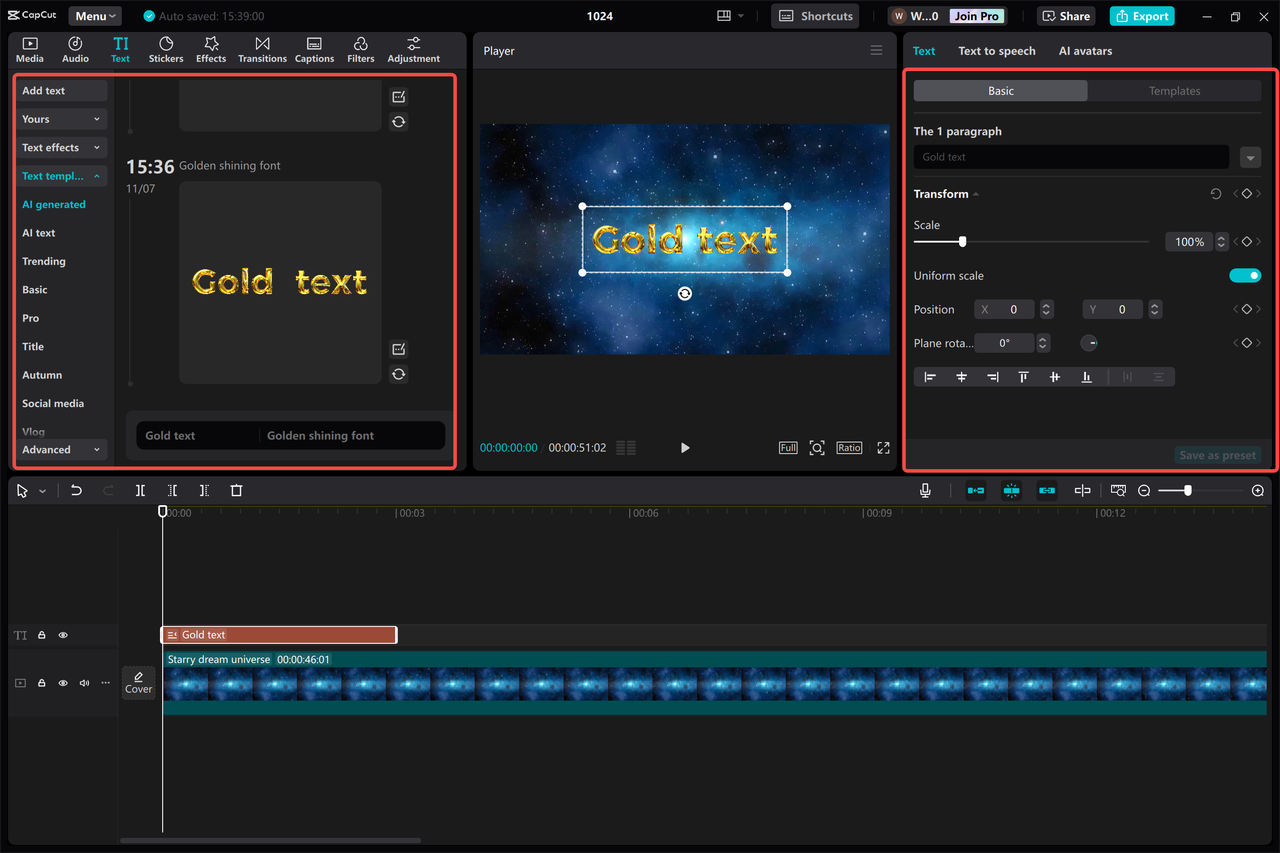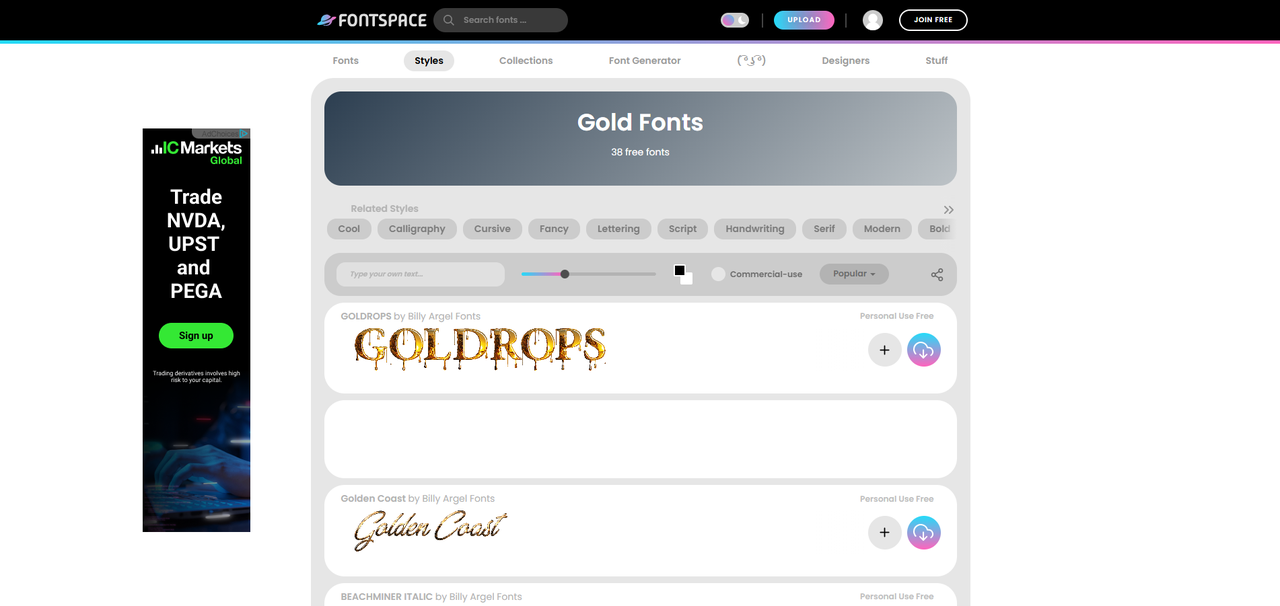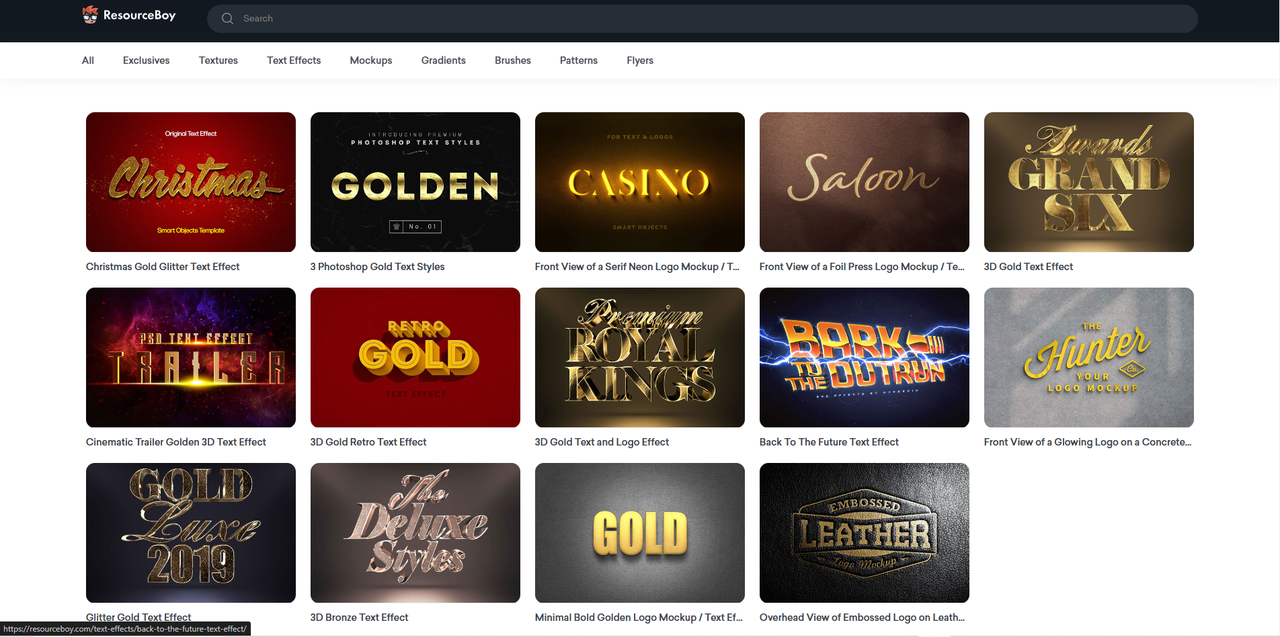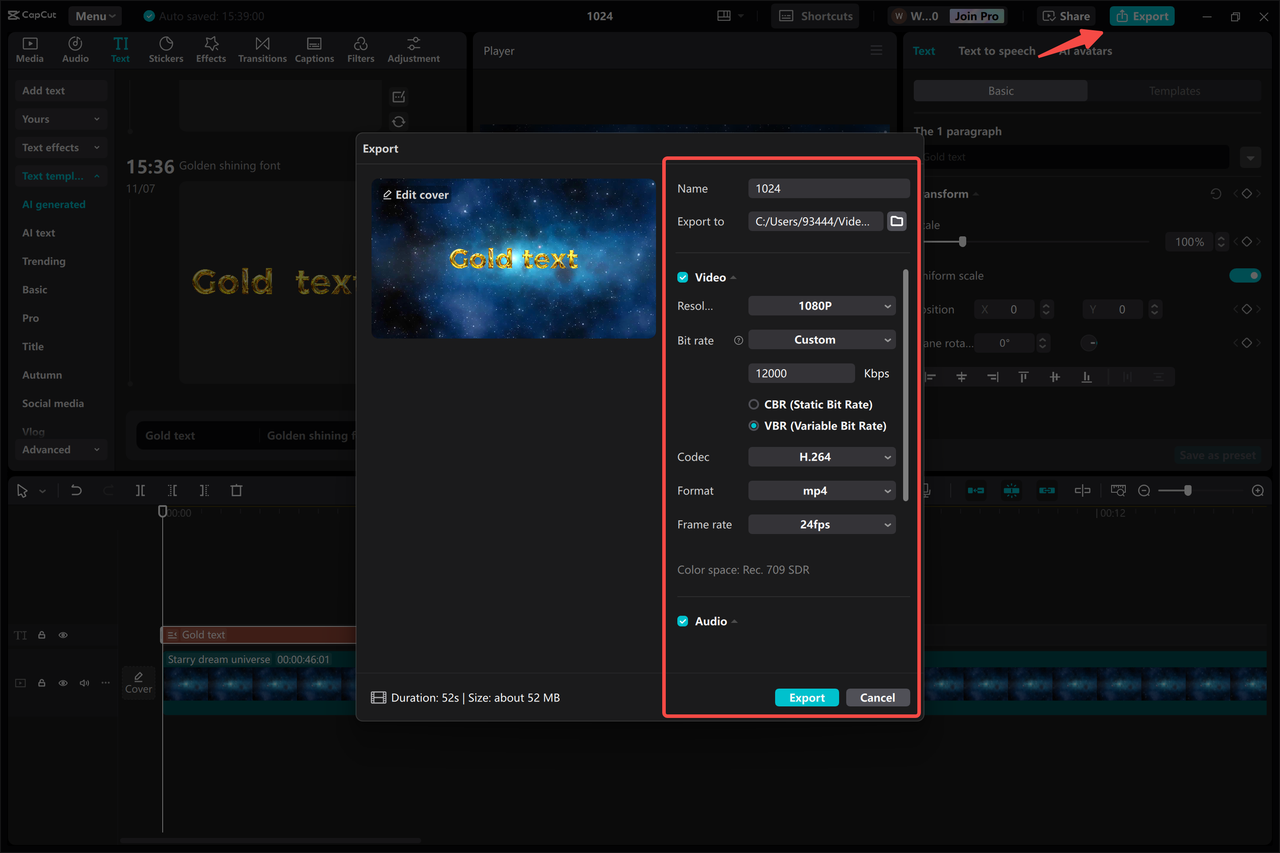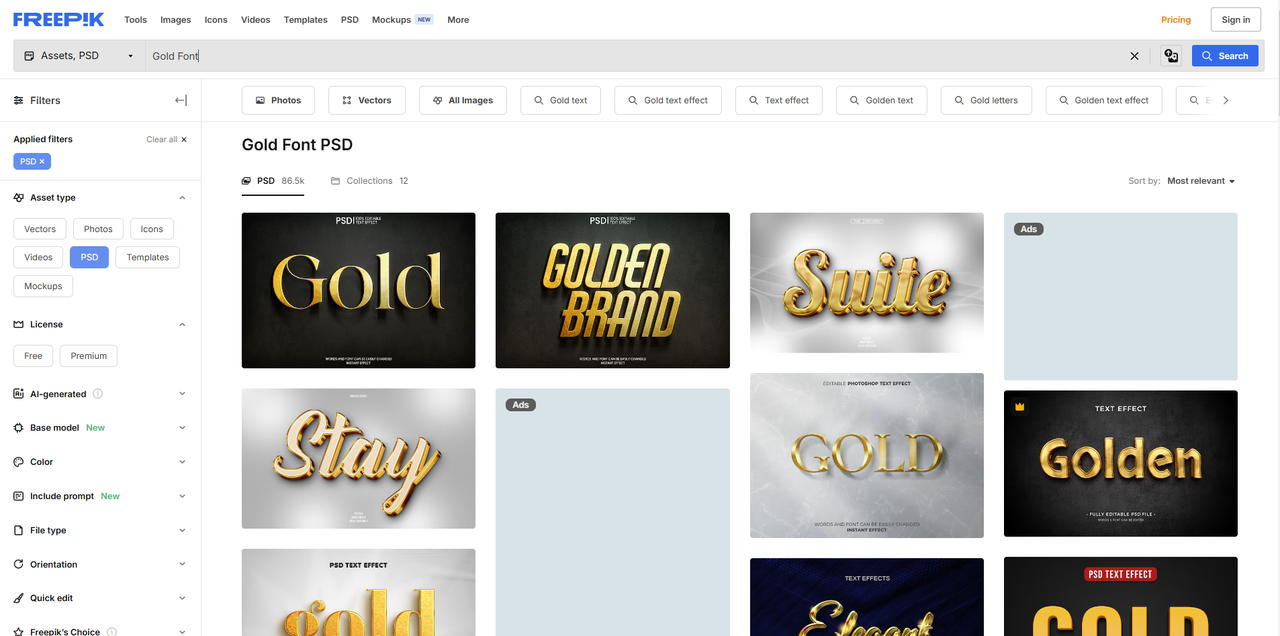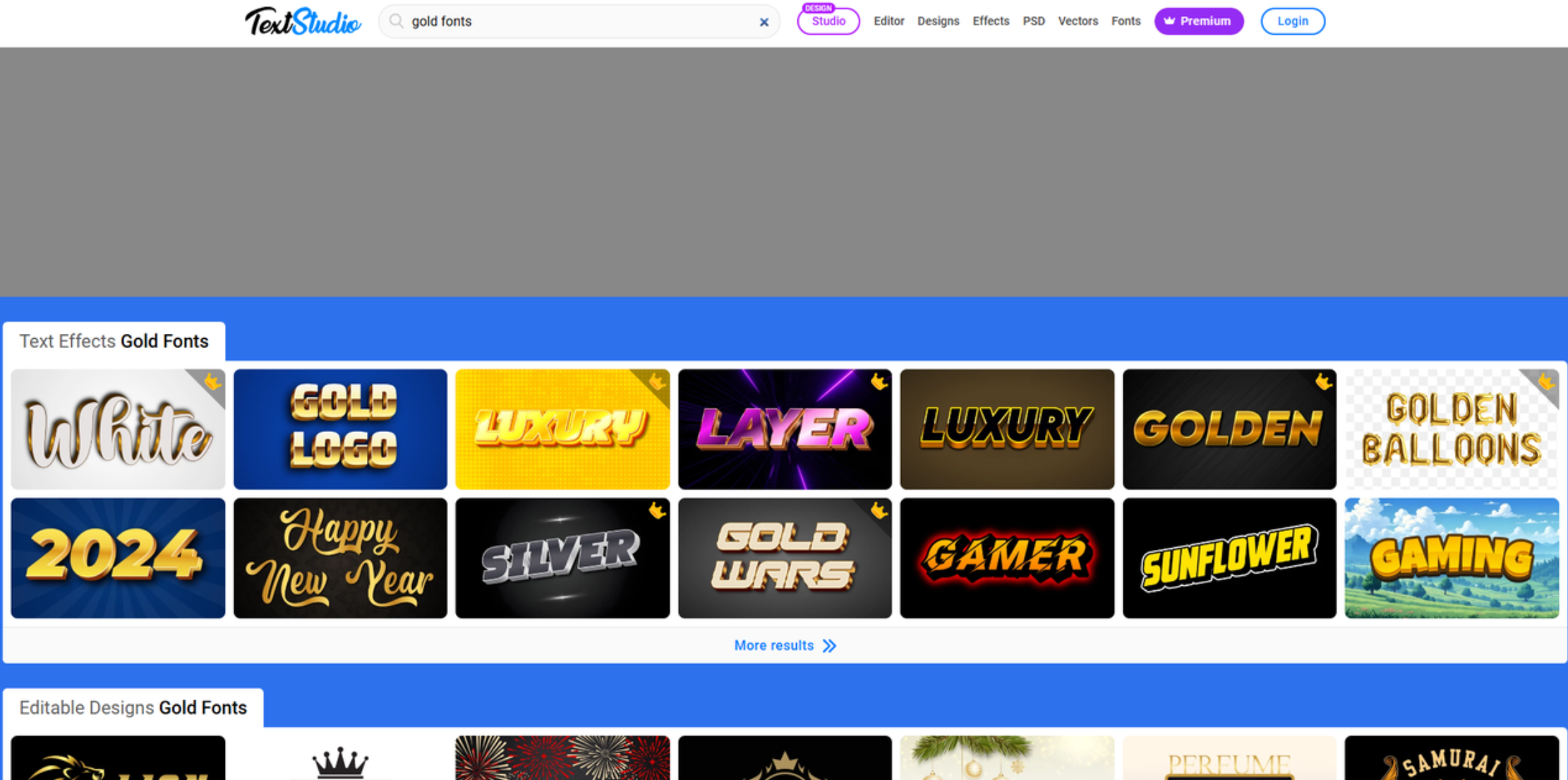
الدليل النهائي لاستخدام الخطوط الذهبية | جعل التصاميم الإبداعية
استكشف خطوط الذهب الرائعة وتعلم كيفية رفع تصميماتك باستخدام الطباعة الجذابة. أضف لمسة من الفخامة إلى رسوماتك بسهولة. علاوة على ذلك ، جرب محرر فيديو سطح المكتب CapCut لتطبيق تأثيرات النص الذهبي السلسة على مقاطع الفيديو وضبطها.
خطوط الذهب
يعد اختيار الخط الصحيح أمرًا مهمًا لكيفية تلقي رسالتك في التصميم والطباعة. تعد الخطوط الذهبية خيارًا شائعًا لإضافة الأناقة والرقي إلى مشاريعك. إنها مثالية للمناسبات التي تريد أن تترك فيها انطباعًا دائمًا.
في هذه المقالة ، سنلقي نظرة على بعض الأفكار الإبداعية لاستخدام نص ذهبي وبعض أفضل الأدوات لتوظيفها لإضافتها إلى المحتوى الخاص بك.
رفع مظهر التصميم الخاص بك مع ألوان الخط الذهب
الآن بعد أن رأينا كيف يمكن أن تكون نصوص الألوان الذهبية جذابة في تصميماتنا ، فلنتعلم كيفية استخدامها بفعالية. تؤدي إضافة هذا النص إلى مشاريعك إلى تباين قوي مع الخلفيات المختلفة ، مما يجعل المحتوى الخاص بك بارزًا. سننظر في عدة طرق لاستخدام النص الذهبي لتحسين تصميمك وإشراك جمهورك!
5 أفكار الخط الذهب الإبداعية
عندما تختار حروفًا ذهبية ثلاثية الأبعاد لتصميماتك ، فإن لكل نمط فوائده بناءً على ما تريد تحقيقه. يمكن للخط الصحيح تحسين مظهر أي شيء ، من الدعوات الرسمية إلى العلامات التجارية الحديثة. فيما يلي 5 أفكار إبداعية لاستخدام النص الذهبي ثلاثي الأبعاد بشكل فعال:
1. سيناريو أنيق للدعوات
يعد استخدام النص الذهبي في نص أنيق خيارًا كلاسيكيًا للدعوات ، خاصة لحفلات الزفاف والمناسبات الرسمية. تضيف الخطوط المتدفقة لخطوط النص الرومانسية والرقي ، مما يجعل دعوتك تشعر بالخصوصية. هذا النمط يعزز الأناقة الشاملة لإعلانات الزفاف.
1. جريئة الرقيق للعلامة التجارية
تعتبر الخطوط الرقيقة الجريئة المصنوعة من الذهب رائعة للعلامة التجارية لأنها تنقل القوة والموثوقية. يمكن أن تؤدي إضافة تأثير نص ذهبي ثلاثي الأبعاد إلى تحسين الرؤية ، مما يمنح علامتك التجارية ميزة فريدة. سواء كان إطلاق منتج جديد أو تغيير العلامة التجارية ، يمكن لخطوط serif الجريئة إنشاء هوية قوية تتواصل مع جمهورك.
1. نمط خمر لتصاميم الرجعية
لإحساس بالحنين إلى الماضي ، تعد الخطوط ذات النمط القديم باللون الذهبي خيارًا جيدًا. غالبًا ما تذكر هذه الخطوط الأشخاص بالماضي وتعمل بشكل جيد مع الحفلات ذات الطابع الخاص أو العلامات التجارية القديمة. يمكن أن يؤدي استخدام خط ذهبي ثلاثي الأبعاد إلى إبراز الخطوط القديمة ، مما يضيف العمق والاهتمام.
1. Sans-serif لجماليات الحد الأدنى
إذا كنت تفضل أسلوبًا نظيفًا وحديثًا ، فإن خطوط sans-serif المصنوعة من الذهب مناسبة للتصاميم البسيطة. هذه الخطوط بسيطة وسهلة القراءة ، مما يجعلها رائعة لمواقع الويب ووسائل التواصل الاجتماعي والعلامات التجارية الحديثة. علاوة على ذلك ، فهو يعمل بشكل جيد مع العلامات التجارية التي ترغب في إظهار صورة حديثة.
1. مكتوبة بخط اليد لمسات شخصية
تضيف الخطوط الذهبية المكتوبة بخط اليد لمسة شخصية لأي تصميم. إنه ممتاز لبطاقات المعايدة أو المدونات الشخصية حيث تريد التواصل مع جمهورك. يمكن أن يؤدي استخدام PSD للنص الذهبي ثلاثي الأبعاد هنا إلى جعل النص يبدو ديناميكيًا وجذابًا.
أفضل 5 طرق مفيدة لتنزيل تأثيرات النص الذهبي المجانية
توفر العديد من الموارد عبر الإنترنت تنزيلات مجانية لتأثيرات النص الذهبي الجميلة. باستخدام هذه التأثيرات ، يمكنك تحسين مشاريعك بسرعة وجعلها تبدو أفضل. فيما يلي 5 طرق مفيدة لتنزيل تأثيرات النص الذهبي المجانية لاحتياجاتك:
1. CapCut محرر فيديو سطح المكتب
يعد محرر فيديو سطح المكتب CapCut أداة سهلة الاستخدام لإنشاء مقاطع فيديو رائعة. يحتوي على العديد من الميزات ، بما في ذلك الرسوم المتحركة النصية الذهبية الأنيقة والتأثيرات التي يمكن إضافتها إلى أي محتوى فيديو. من خلال تخطيطه البسيط ، يمكنك تخصيص النص بسرعة وجعل مقاطع الفيديو الخاصة بك جذابة بصريًا. يحتوي هذا البرنامج أيضًا على أدوات تخصيص فيديو أخرى للحصول على مظهر نهائي محسّن.
Interface of the CapCut desktop video editor - an easy way to add gold text to videos on PC
السمات الرئيسية
يحتوي محرر فيديو سطح المكتب CapCut على العديد من الميزات التي تسهل إضافة نص إلى مقاطع الفيديو الخاصة بك . فيما يلي بعض من أفضلها:
• المدمج في تأثير النص الذهب
تطبيق على الفور جميلة تأثيرات النص الذهب لمشاريعك ، إضافة لمسة من الأناقة دون الحاجة الإضافات إضافية.
• قابل للتعديل الظل وخيارات توهج
قم بتحسين رؤية النص الخاص بك عن طريق تخصيص إعدادات الظل والتوهج ، وخلق العمق ، وجعل النص الذهبي الخاص بك بارزًا.
• الانتهاء من المعدن مع وسائط مزيج
حقق مظهرًا معدنيًا واقعيًا للنص باستخدام أوضاع مزج مختلفة ، مما يتيح لك مطابقة التأثير مع خلفيات مختلفة بسلاسة.
• تحرير نص طبقة مرنة
قم بتحرير طبقات النص وترتيبها بسهولة في مشروعك ، مما يمنحك تحكمًا كاملاً في التصميم ويضمن وضع النص الذهبي بشكل مثالي.
• مواضع نص مخصص
ضع النص الذهبي في أي مكان على الشاشة بدقة. يضمن ذلك تخطيطات إبداعية تعزز جمالية الفيديو بشكل عام ، خاصة عند إضافة ترجمات مصاحبة إلى الفيديو .
كيفية إضافة الخطوط الذهبية إلى مقاطع الفيديو في CapCut
لإضافة خطوط ذهبية إلى مقاطع الفيديو الخاصة بك في CapCut ، قم أولاً بتنزيل البرنامج وتثبيته من الموقع الرسمي. بمجرد التثبيت ، افتح CapCut وأنشئ مشروعًا جديدًا. يمكنك بسهولة تطبيق الخطوط الذهبية عن طريق تحديد خيارات النص وتخصيصها بالتأثيرات المضمنة. يمكنك تنزيله بالنقر فوق زر التنزيل أدناه: